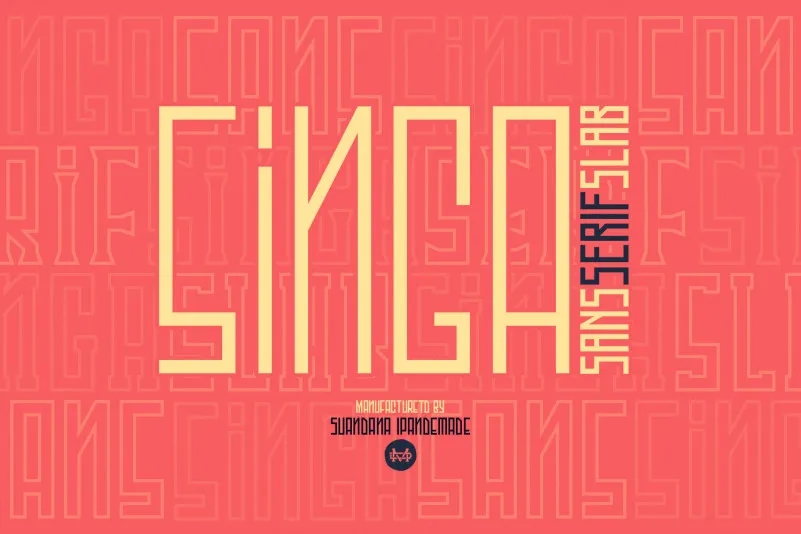
Este tipo de letra é uma família com três estilos distintos de casual clássico que vem com 9 pesos variáveis para criar uma diversidade incrível de efeitos e intensificar seu design. É perfeito para aqueles profissionais digitais ou designers gráficos buscando algo leve, moderno e ainda muito elegante. As variações de peso permitem um toque mais suave, uma aparência alegre e até mesmo um ar sofisticado dependendo do contexto. Com apenas esse único arquivo de fonte, você pode adaptá-lo para diferentes usos sem precisar baixar ou instalar outro tipo diferente. Este tipo de letra feita especialmente por madeDeduk é perfeita para qualquer projeto que exija uma personalização única, seja em cartazes, websites, logotipos ou impressões. É um verdadeiro aperitivo para seu próximo design, oferecendo ao mesmo tempo elegância e versatilidade. Não deixe de experimentar essa fonte moderna e divertida.